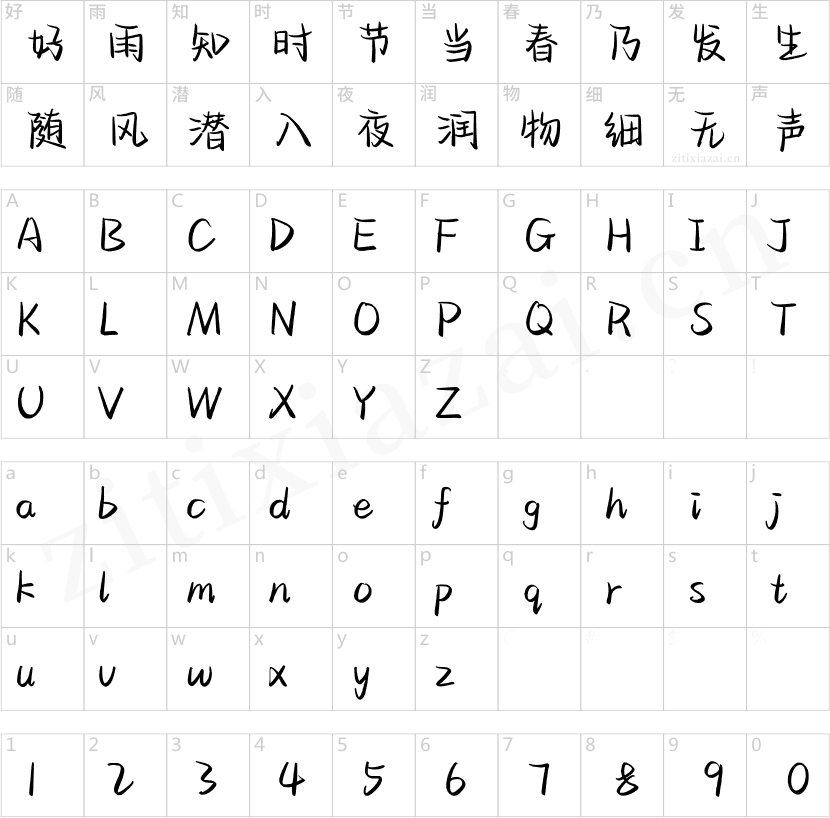
Aa漫语手写体
Aa漫语手写体字体
Aa漫语手写体是一款非常具有艺术性的字体,它的设计灵感来源于对古典艺术的研究,同时又融入了现代字体设计的元素。字形优美,笔画粗细变化自然,给人以大气、典雅的感觉。Aa漫语手写体是一款既传统又现代的字体,它的设计充满艺术感,美观大方,实用性也非常强。无论是对于设计师还是对于普通读者来说,都是一种非常不错的字体选择。Aa漫语手写体适合用于具有艺术感的场合,比如海报、宣传单张、书籍封面等。由于其字形流畅且具有动态感,也适合用于大量的文本排版,如报纸、杂志等。